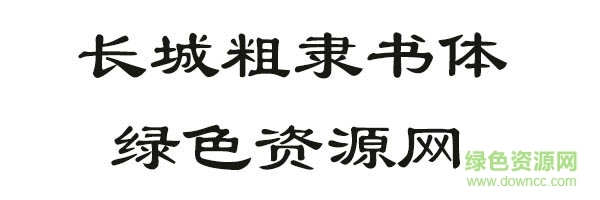
長城粗隸書體
長城粗隸書體是一款筆畫中粗的簡體隸書字體。該字體給人的感覺是,部分筆畫更粗點,總體還是很有韻味的。趕快到綠色資源網(wǎng)下載體驗吧!
長城粗隸書體介紹
隸書是漢字中非常常見的一種莊重的字體,書寫呈現(xiàn)的效果寬扁,橫畫長而直畫短,呈長方形狀,講究“蠶頭雁尾”、“一波三折”。隸書起源于秦朝,由程邈整理而成,在東漢時期達到頂峰,書法界有“漢隸唐楷”之稱。